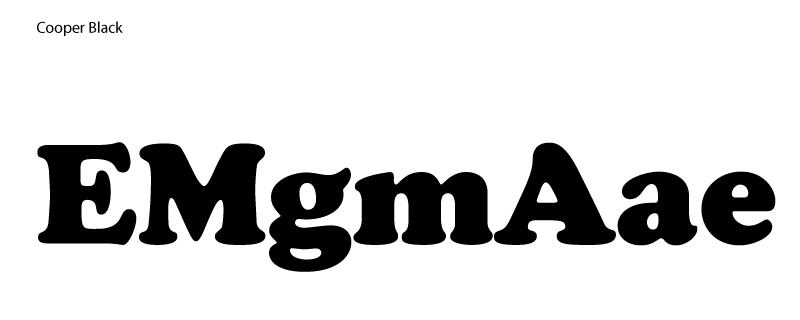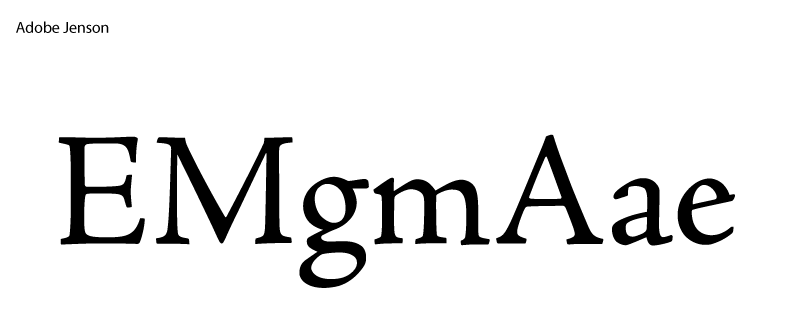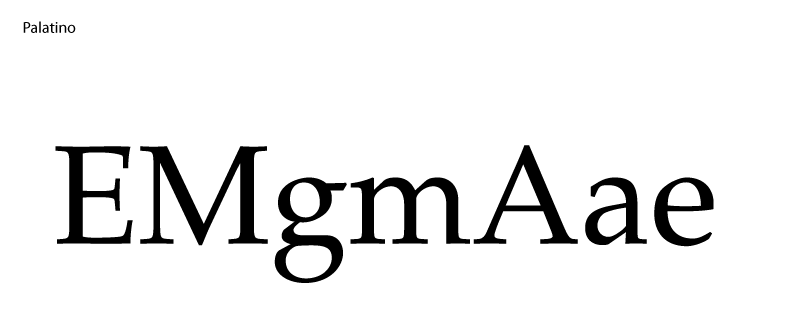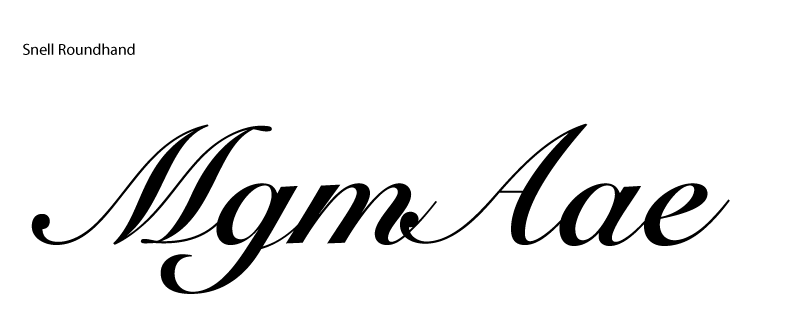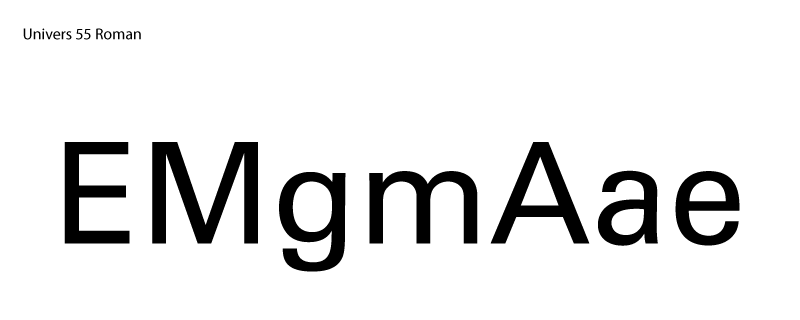
| Humanistische
Schriften (Venezianische Renaissance-Antiqua)
Horley Old
Style, Jenson-Eusebius, Cloister, Kennerley
| Garalde
Schriften (Französische
Renaissance-Antiqua)
Sabon,
Garamond, Bembo, Times New Roman, Plantin,
Palatino, Caslon Old Face
| Übergangsschriften |
Baskerville,
Caslon, Fournier, Perpetua
| Didone
Schriften (Klassizistische Antiqua)
Bauer Bodoni,
Bodoni, Torino, Walbaum
| Neue Übergangsschriften
mit Serifen
Bookman,
Century Schoolbook, Cheltenham
| Slab Serif
(serifenbetonte Linear Antiqua / Mécanes-Schriften)
Clarendon,
Memphis, Serifa, Calvert
| Linéale-Schriften
A Grotesk (ohne Serifen)
Franklin
Gothic, News Gothic, Trade Gothic
| Linéale-Schriften
B Neo-Grotesk (ohne Serifen)
Akzidenz
Gothic, Folio, Helvetica, Univers
| Linéale-Schriften
C Geometrisch
Futura,
Kabel, Eurostile, Avant Garde
| Linéale-Schriften
D Humanistisch
Gill Sans,
Optima, Goudy Sans, Rotis Sans Serif
Incises-Schriften (Antiqua Varianten)
Albertus,
Fritz Quadrata, Trajan, Amerigo
Handschriftliche Antiqua (Manuaires Schriften)